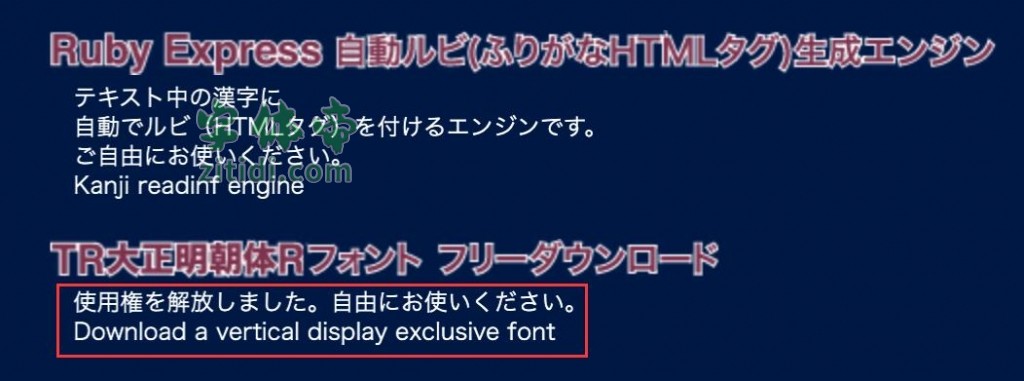
TR大正明朝体Std字体信息
TR大正明朝体是一款漂亮的日系免费商用古典明朝体。这款字体发布于2011年,距离现在年代比较久远。这款字体的开发公司在2014年消失了,但是这款字体使用权已被释放,现在可以随意使用它。
“TR大正明朝体Std”是一款书写很新颖的字体,字体大方,适合各种设计作品使用!欢迎下载!